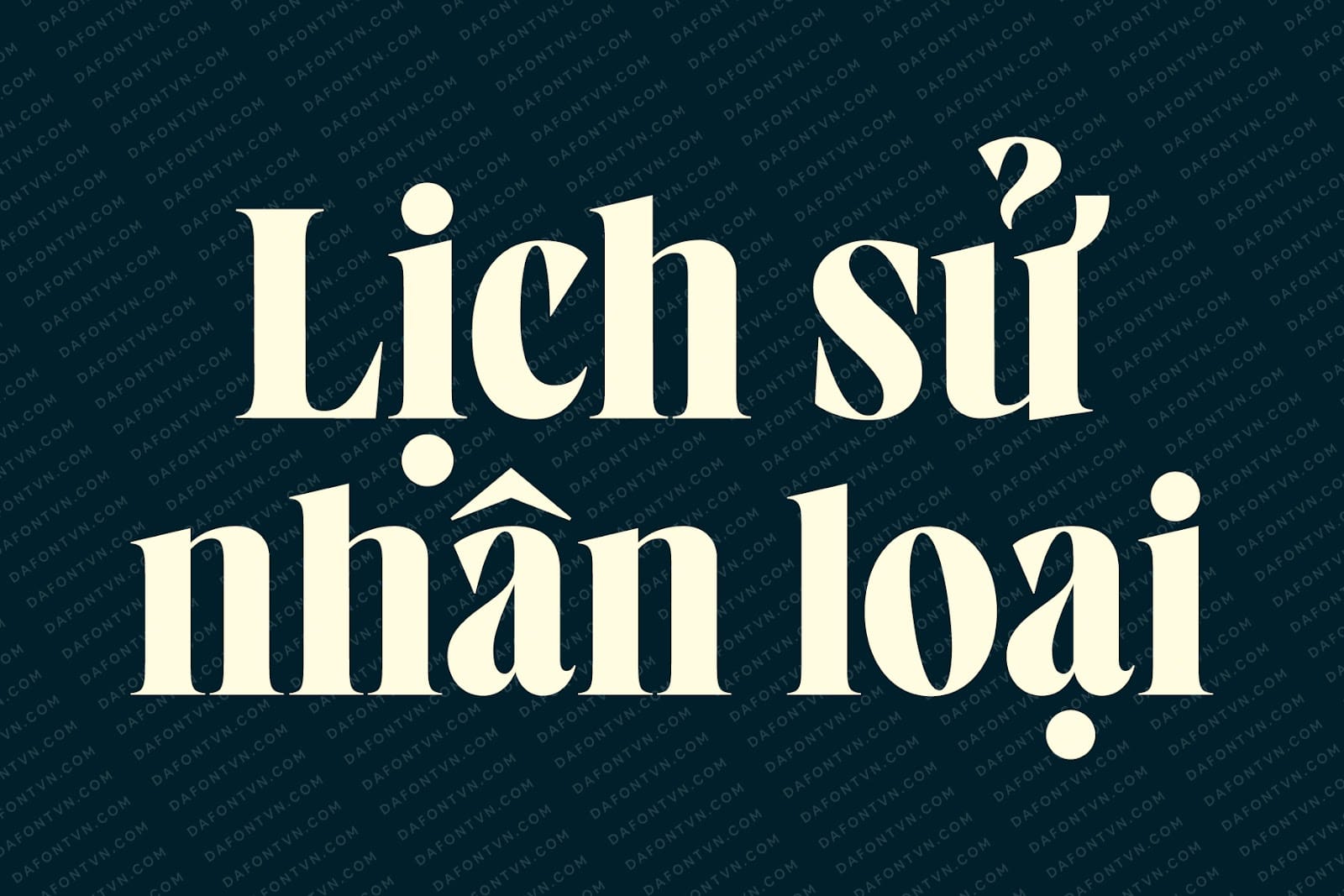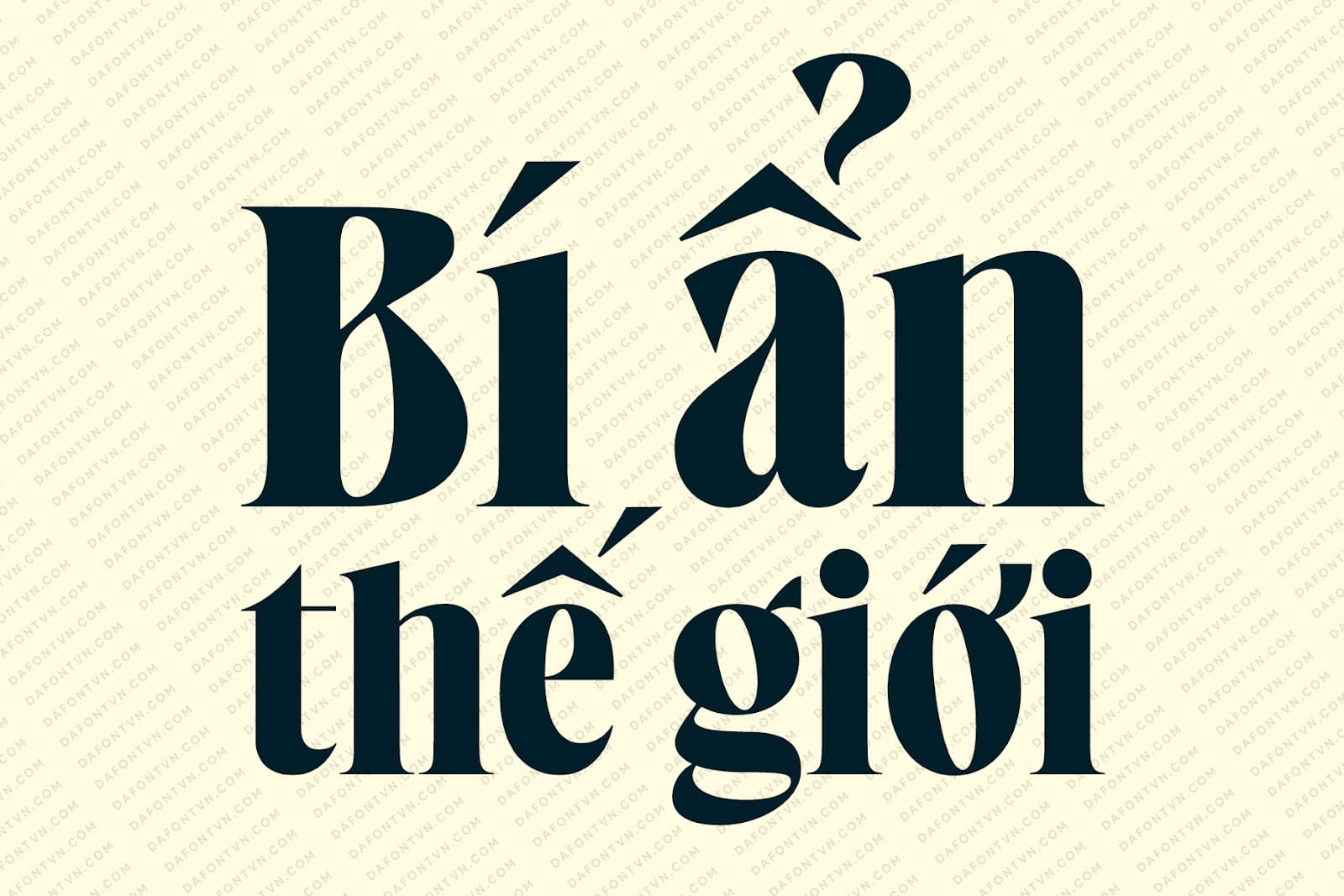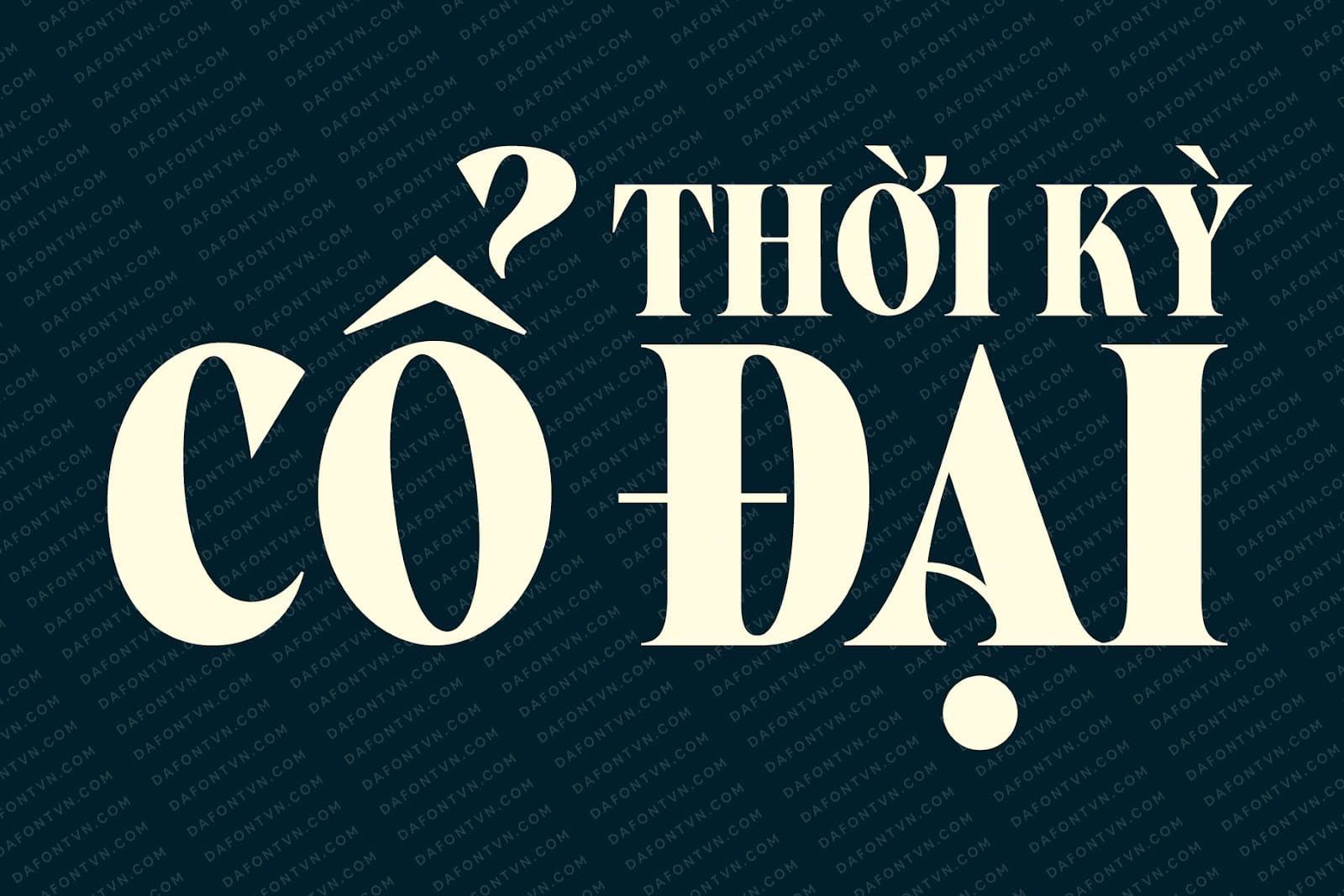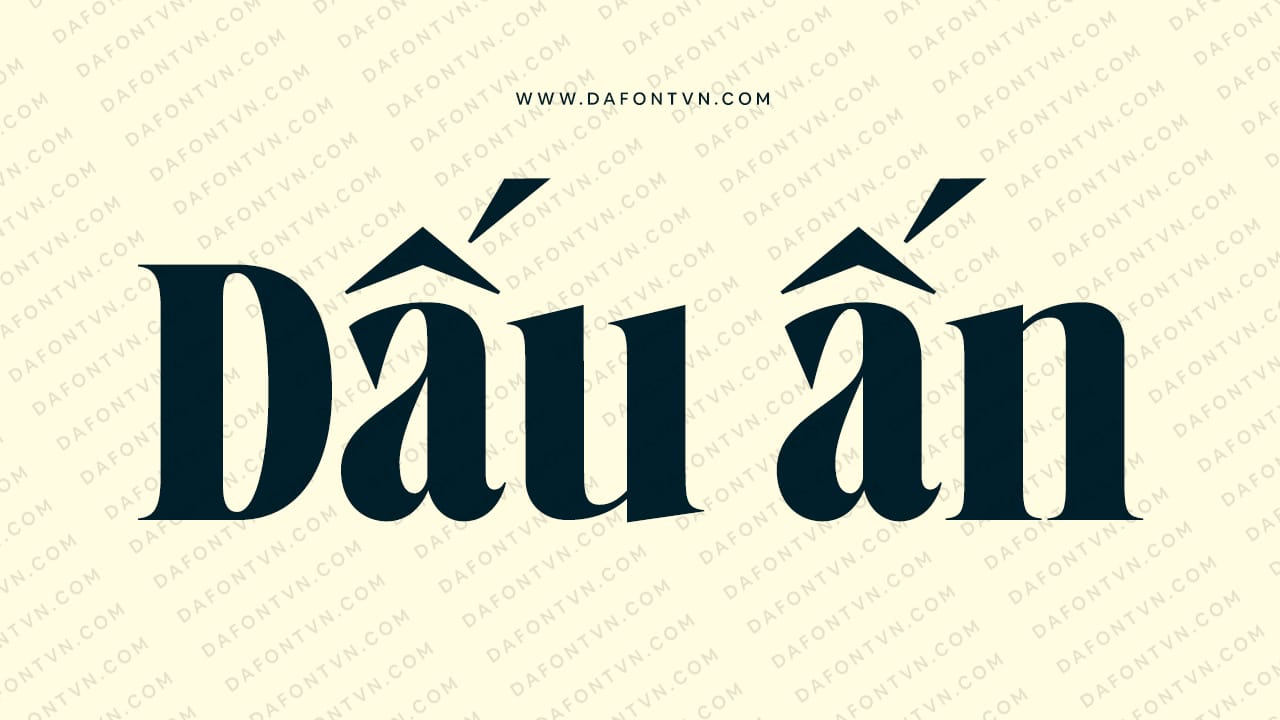
West West font là một kiểu chữ serif có độ tương phản cao với chiều cao lớn giúp nó phù hợp cho việc hiển thị có thể sử dụng cho tiêu đề, báo chí, tạp chí, poster, quảng cáo, ứng dụng.Khi sử dụng font West West ở kích thước lớn, bạn sẽ thấy nó hiển thị rất tốt và nổi bật, ngoài ra các nét chữ của nó mang một chút gì đó cổ điển. Với một số hình dạng theo phong cách Art Nouveau và độ tương phản lớn, West West là lựa chọn tuyệt vời ở bất cứ thiết kế nào dành cho bạn cần một kiểu chữ phong cách và thời trang.